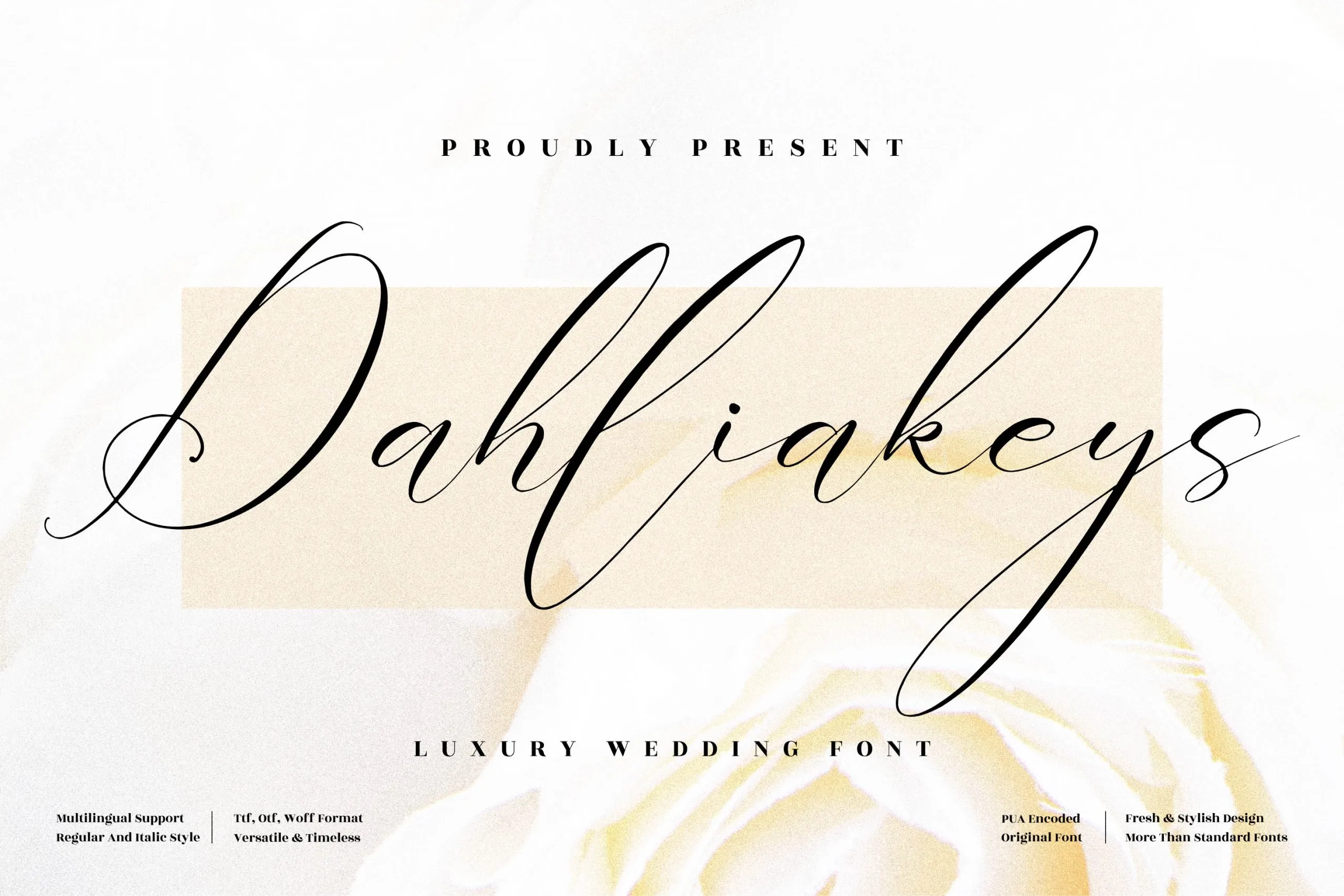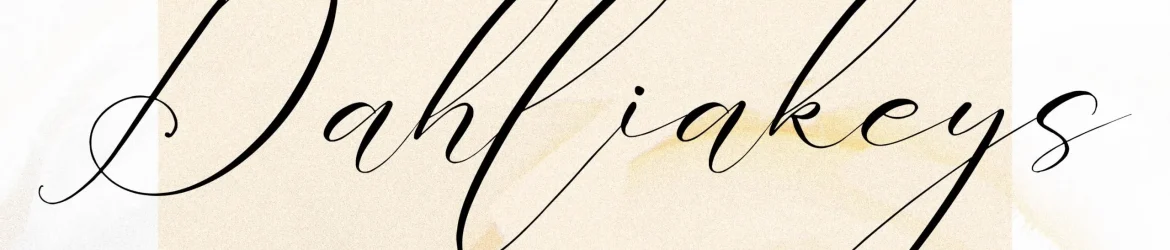
Dahliakeys Font – Download Grátis
A fonte ‘Dahliakeys Font’ é perfeita para aqueles que desejam adicionar uma pitada romântica aos seus projetos de design. Esta elegante tipografia cursive, desenvolvida pelo designer perspectype, é ideal tanto para criações gráficas como logomarcas e identidades visuais, como também para designs de produto, embalagens, arte em papel, publicidade, entre outros. A sua utilização varia desde as etiquetas e cartões de visita até à capa de um livro ou até mesmo uma decoração especial para eventos especiais. Com a ‘Dahliakeys Font’, você pode incorporar um toque único e delicado aos seus trabalhos, transformando o básico em algo extraordinário. É perfeita para qualquer projeto que desejem destacar-se com um texto elegante e poético. Seja para criar cartazes inspiradores, ou mesmo para adicionar uma personalidade autêntica a suas fotografias de forma a torná-las mais memoráveis, ‘Dahliakeys Font’ tem o poder de fazer toda a diferença no seu design.